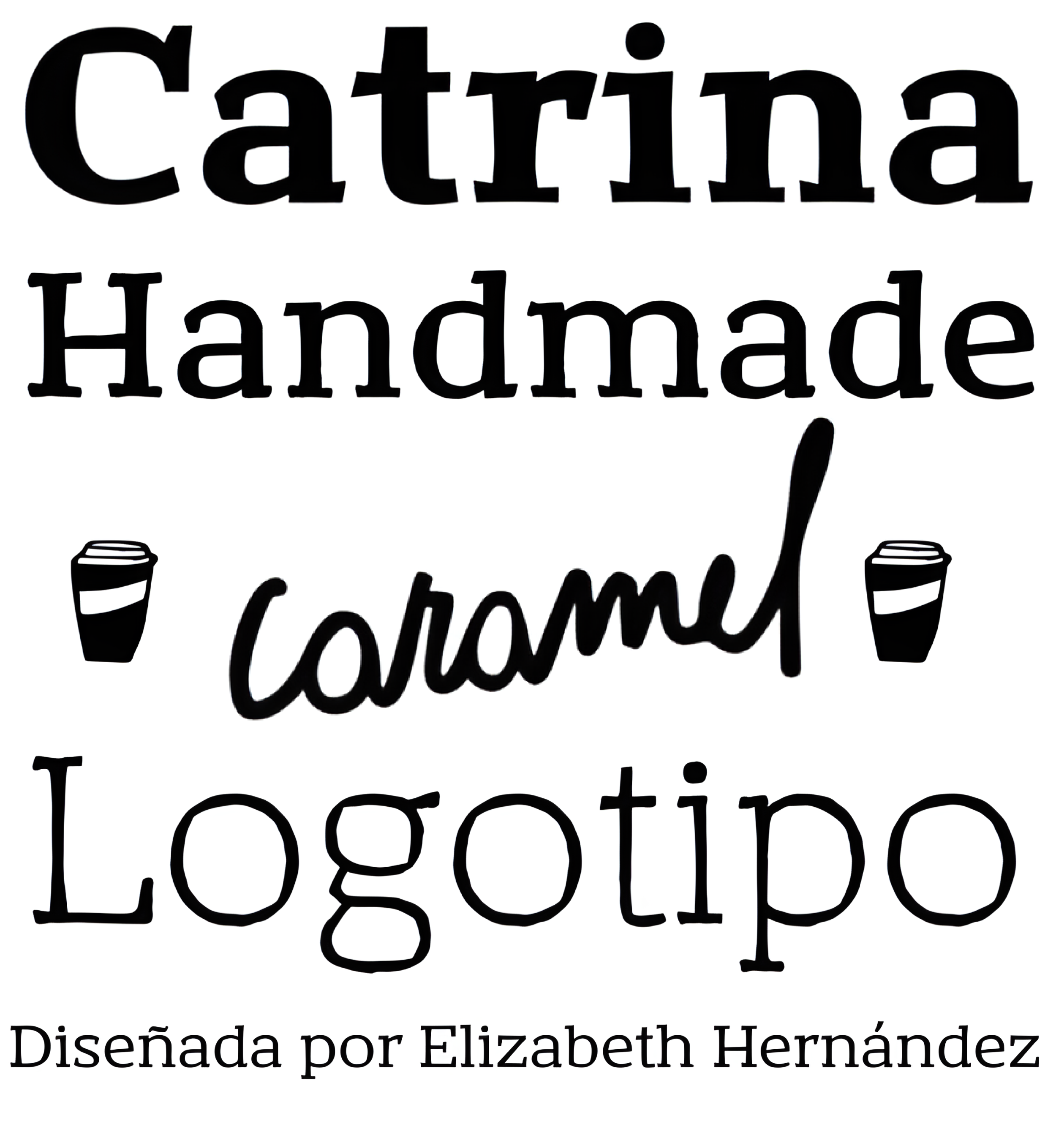
Catrina
| Año | 2017 |
| Créditos | Elizabeth Hernández |
| Descripción | Catrina, diseñado por Eli Hernández, es un tipo de letra expresivo cuyas curvas y líneas rectas se encuentran en armoniosa sincronía. Catrina se presenta en 6 pesos, que van del fino al negro, además de una versión Handmade, e incluye Dingbats y Catchwords que la convierten en la elección perfecta para envases, marcas, títulos y publicidad. |
| Clasificación | Títulos, Dingbats |
| Familia(s) | Catrina |
| Estilos | 14 |
| Set | Especializado |